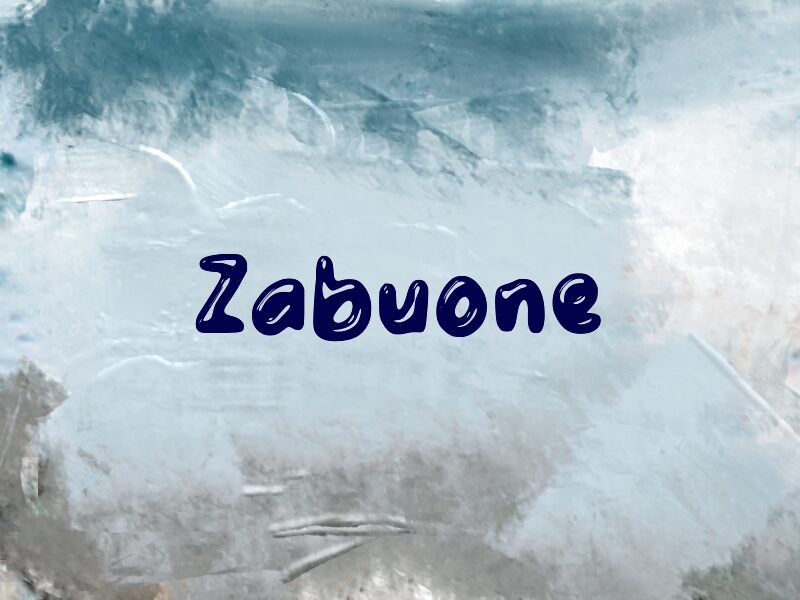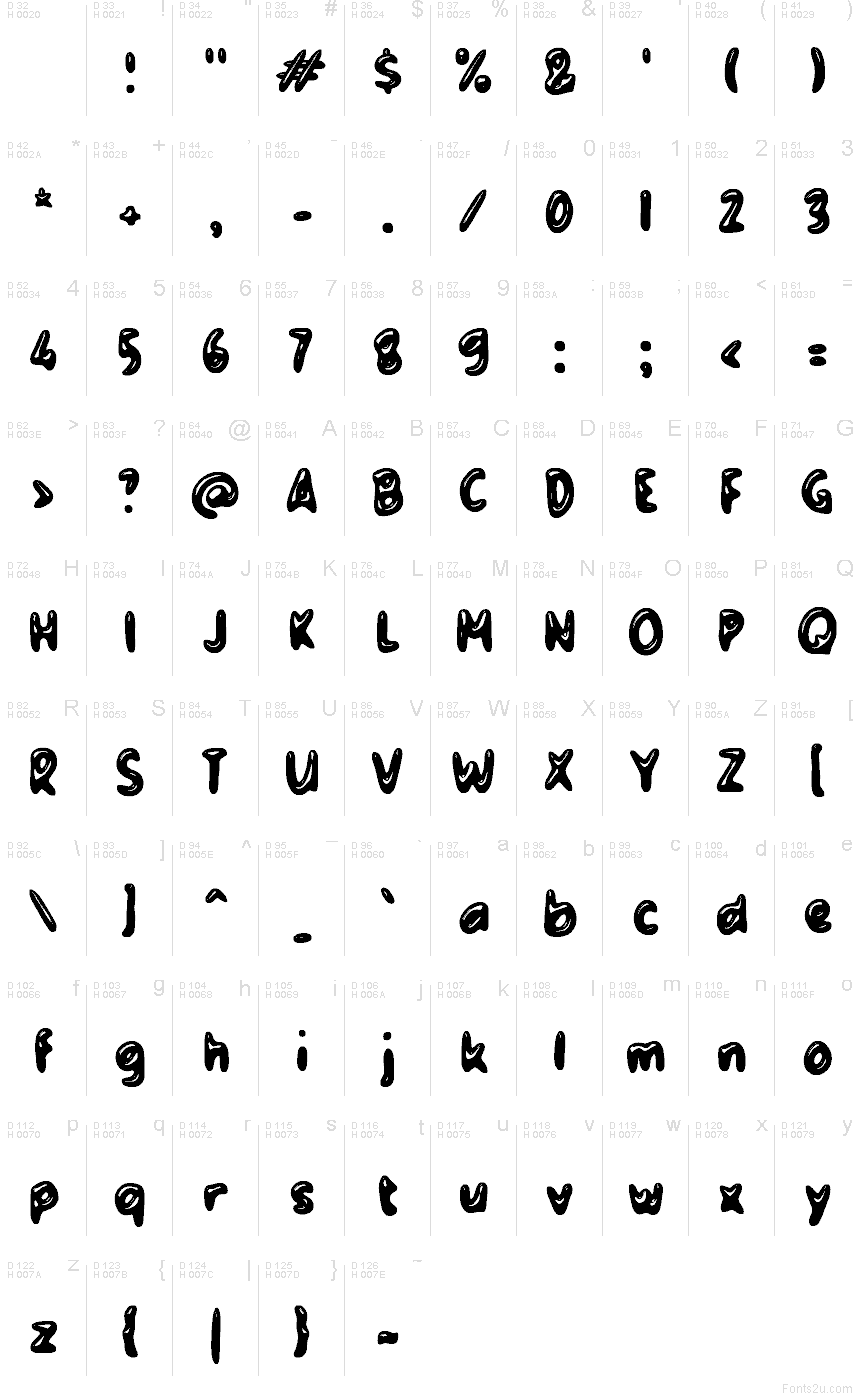
Zabuone
Zabuone от Wep - это бесплатный акцидентный шрифт в мультяшном стиле, состоящий из надутых черных букв. Мягкие, обтекаемые формы и яркие блики делают каждый знак блестящим и объемным. Этот «надутый» силуэт придает шрифту игривый, пружинистый характер, поэтому дизайн выглядит скорее как лепные фигурки, чем как обычный шрифт для заголовков.
Zabuone отлично подходит для обложек детских книг, комиксов, упаковки снеков, приглашений на день рождения и веселых постов в соцсетях, создавая радостное настроение в мгновение ока. Округлые формы и яркие акценты оживляют короткие слова, что делает этот шрифт идеальным выбором, когда нужно, чтобы заголовки или значки выглядели мягко, дружелюбно и немного по-мультяшному крупно.